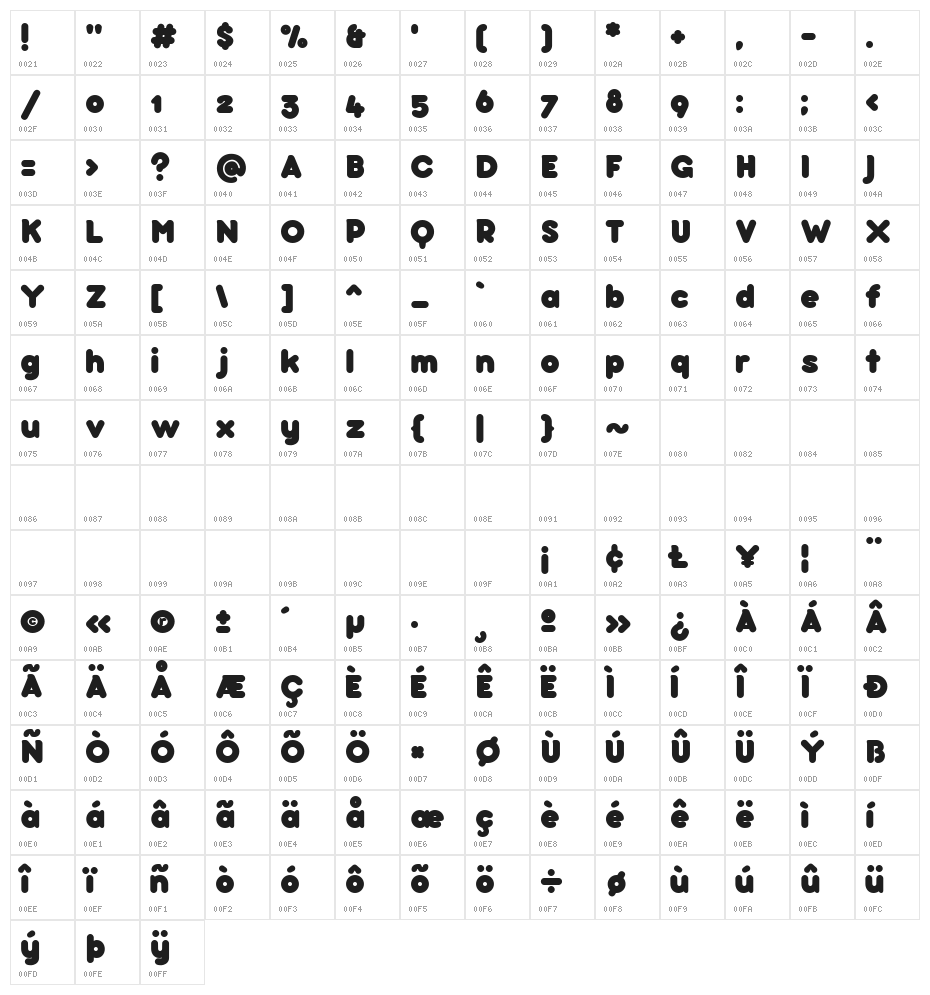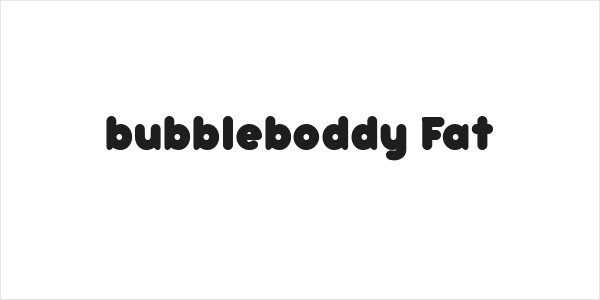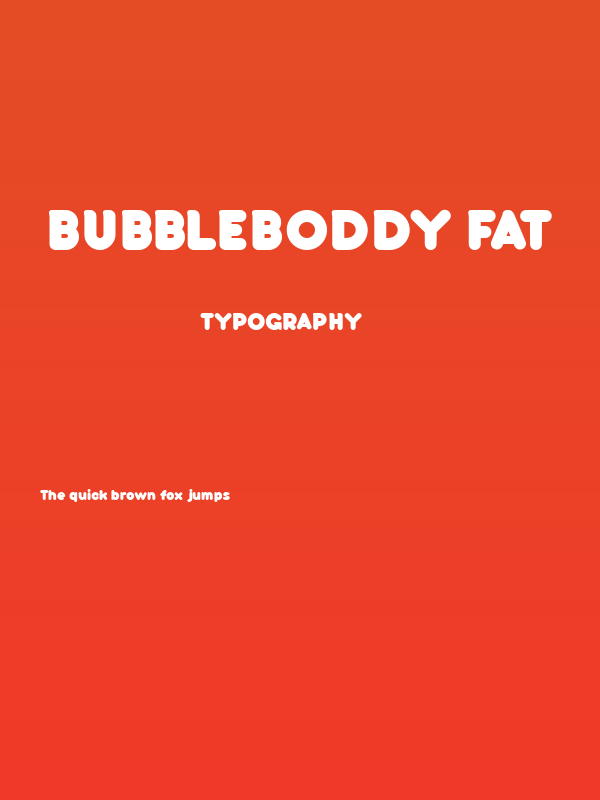
bubbleboddy Fat Font
| Gesamtstil | Playful |
| Vorgeschlagene Projekte | Ideal for children's books, playful branding, party invitations, and casual posters. |
bubbleboddy Fat